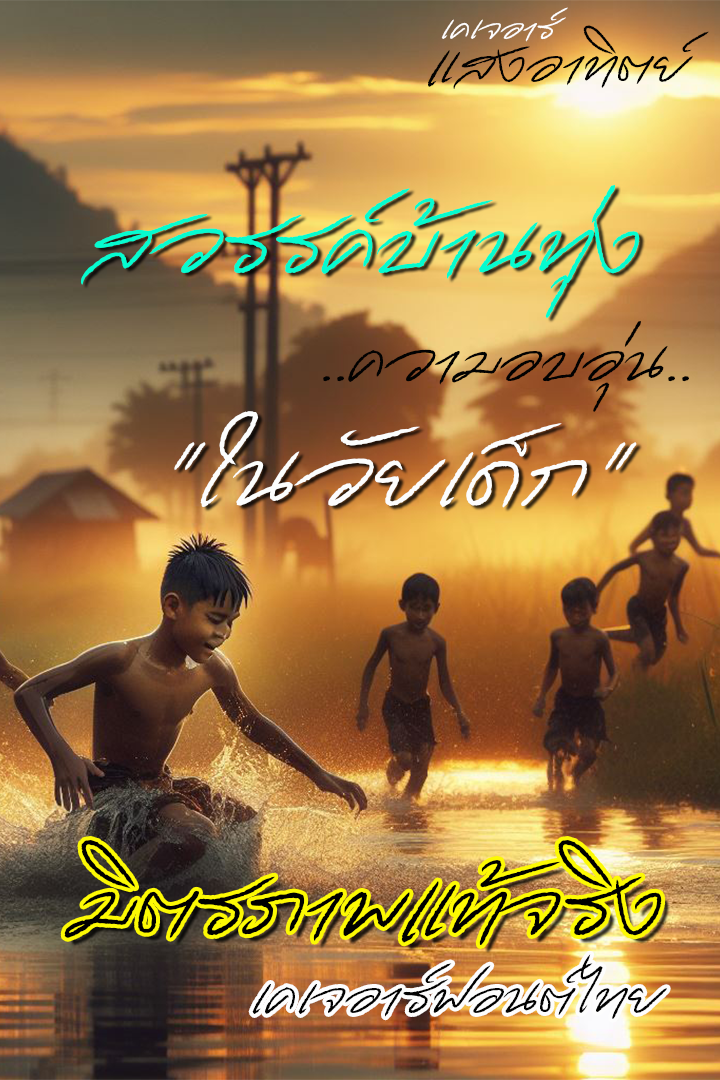
เคเจอาร์ แสงอาทิตย์ (KJR SANG_ARTID)
ฟอนต์ลายมือแนวบรัช เหมาะกับการใช้งานทัวไป ประกอบคลิปวีดีโอต่างๆก็สวยงาม ฟอนต์ชุดนี้เป็นตัวทดลองให้ใช้นะครับนะครับ ติดบัคเยอะหน่อยต้องขออภัยครับ